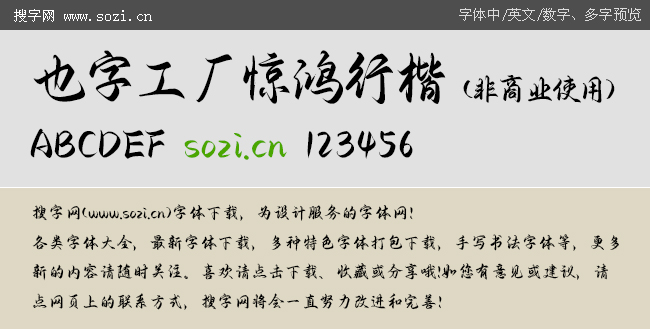
也字工廠驚鴻行楷
搜字網(wǎng)給大家提供一款也字工廠驚鴻行楷(非商業(yè)使用)中文字體下載,也字工廠驚鴻行楷是一款手寫書法字體,字體書寫簡潔流暢,字形端正自然。具有很好的視覺效果。適合應用于藝術設計、平面宣傳設計、網(wǎng)頁設計、海報設計等應用(此字體為個人非商用版,商用可以聯(lián)系:官方網(wǎng)址:https://yefont.com/home,聯(lián)系方式:13798980448)。